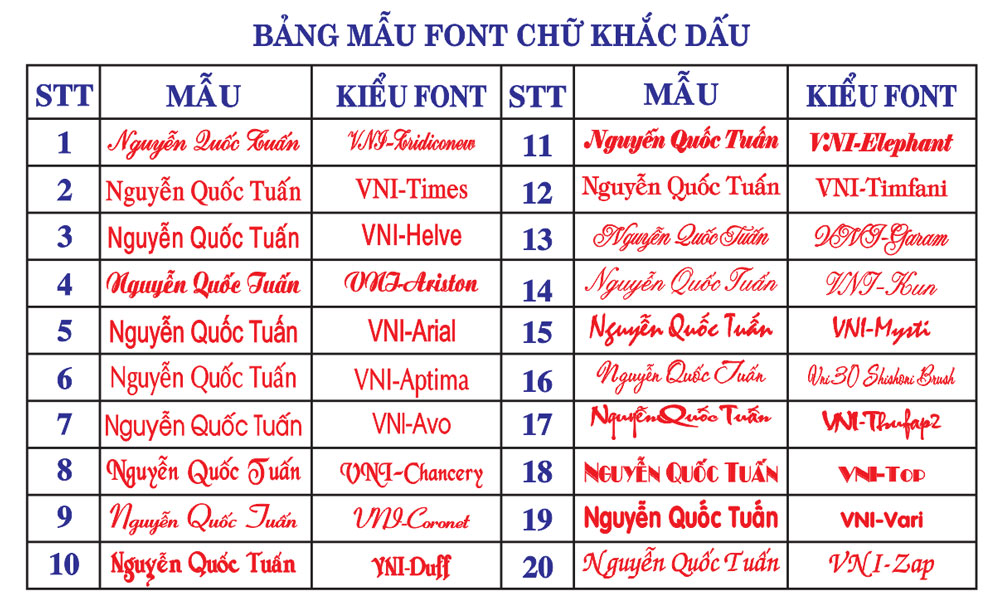
Font chữ con dấu là nhóm phông chữ kỹ thuật chuyên dùng trong lĩnh vực khắc dấu cao su, khắc laser mộc dấu công ty, dấu chức danh và các mẫu dấu phê duyệt bản vẽ hoàn công. Sở hữu cấu trúc nét chữ gọn gàng, độ dày nét chuẩn xác và tính chuẩn mực cao, việc sử dụng đúng font chữ làm con dấu giúp các kỹ sư, kiến trúc sư và doanh nghiệp thể hiện tính pháp lý minh bạch trên các hợp đồng thi công, biên bản nghiệm thu hay hồ sơ thiết kế nhà lắp ghép.
Độ sắc nét và cấu trúc kỷ luật của các dòng font chữ con dấu
Điểm giá trị của dòng font con dấu nằm ở tính dễ đọc và khả năng chịu lực cơ học khi chuyển đổi thành dạng con dấu cao su hoặc con dấu liền mực. Khác với các phông chữ trang trí rườm rà, các kiểu chữ dùng để khắc dấu thường sở hữu các đường thẳng dứt khoát, không có chân phụ thừa thãi hoặc sử dụng dạng chữ thảo mực thước đối với con dấu chữ ký.
Sự ổn định về mặt thị giác của dòng font này giúp khẳng định tính xác thực và thẩm quyền của người ký duyệt hồ sơ. Khi xuất hiện trên các góc bản vẽ kỹ thuật CAD dưới dạng con dấu vuông thẩm tra hay mộc tên chức danh kỹ sư giám sát, phông chữ mang lại cảm giác nghiêm túc, chuẩn mực.
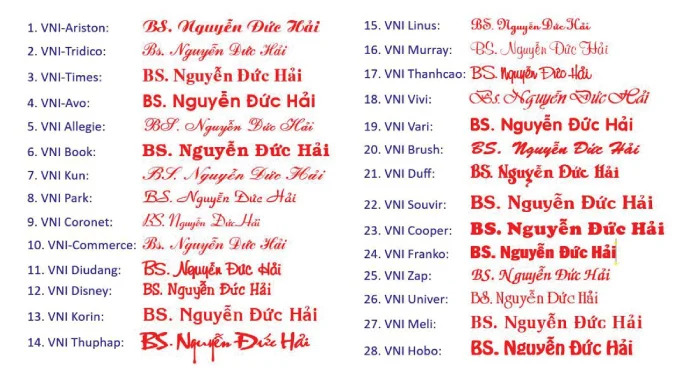
| Nhóm con dấu | Đặc tính phông chữ | Mục đích phù hợp |
|---|---|---|
| Dấu tròn doanh nghiệp | Sans-serif đứng, nét đều, gọn gàng | Font chữ con dấu tròn pháp nhân |
| Dấu tên & Chức danh | Chữ thảo mềm mại hoặc chữ in hoa đậm | Font chữ làm mộc tên, chức danh |
| Dấu vuông hoàn công | Condensed Sans, nét hẹp, rõ ràng | Font chữ con dấu vuông bản vẽ |
| Dấu chức vụ kiểm tra | Serif truyền thống hoặc Sans-serif dứt khoát | Dấu đã thu tiền, dấu sao y bản chính |
Tư vấn từ chuyên viên: Khi thiết kế font chữ khắc dấu tròn pháp nhân, bạn nên sử dụng các kiểu chữ không chân dạng đứng (như Arial hoặc Helve) để thông tin công ty uốn cong theo đường tròn được sắc nét.
03 Ứng dụng font con dấu vào công tác quản lý xây dựng
Nhờ tính chuẩn mực và độ nhận diện pháp lý cao, bộ phông chữ này mang lại giá trị thực tế lớn trong khâu hành chính và quản lý thi công công trình hiện đại:
- Khắc dấu mộc tên cho Kỹ sư và Kiến trúc sư: Những nét chữ mực thước của font chữ con dấu tên giúp các cán bộ kỹ thuật đóng dấu xác nhận lên các bản vẽ hiện trường, nhật ký thi công nhà lắp ghép một cách rõ ràng và uy tín.
- Làm dấu vuông Phê duyệt và Hoàn công bản vẽ: Phông chữ dạng condensed khi khắc lên con dấu vuông khung viền sẽ giúp các thông tin về ngày nghiệm thu, đơn vị tư vấn giám sát hiển thị trọn vẹn trong các khung tên bản vẽ AutoCAD.
- Khắc dấu tròn pháp nhân cho Doanh nghiệp: Áp dụng font chữ đóng dấu chuẩn quy định giúp con dấu doanh nghiệp khi đóng lên hợp đồng kinh tế đạt độ sắc sảo, không bị nhòe mực trên các chất liệu giấy in thông dụng.
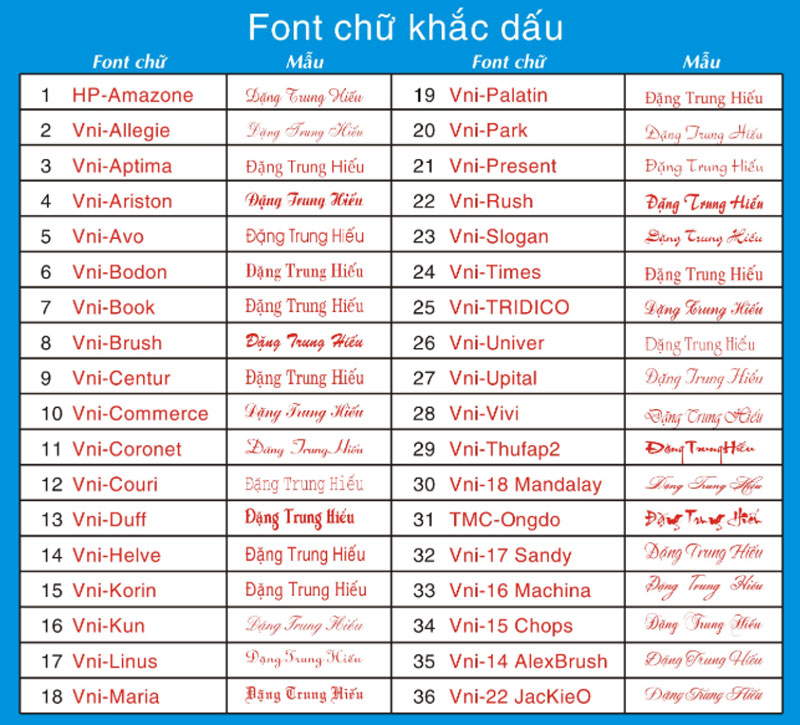
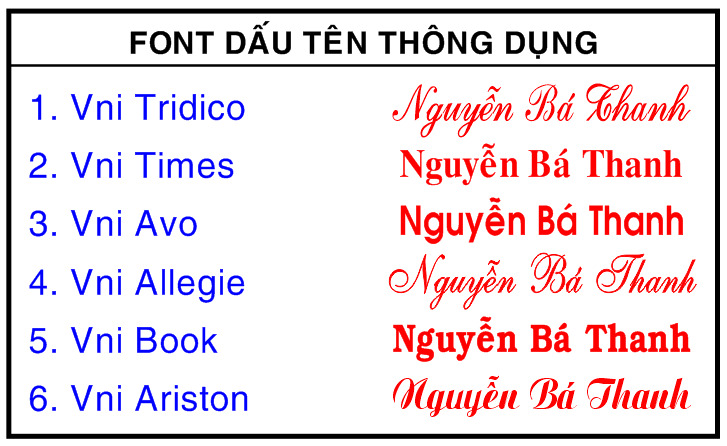
03 Lưu ý bố cục font chữ khắc dấu tên và dấu tròn rõ nét
Để con dấu sau khi gia công cơ học đạt độ sắc nét và không bị lem mực khi sử dụng thực tế, người thiết kế nên lưu tâm một số kinh nghiệm sau:
- Kiểm soát độ dày nét chữ: Khi lập trình khắc laser cao su, nét chữ không được quá mảnh vì sẽ dễ bị đứt gãy dưới lực ép đóng dấu, nhưng cũng không được quá dày vì sẽ hút nhiều mực dầu gây hiện tượng bết dính các chữ cái có vòng kín (như o, e, a).
- Bố trí khoảng cách chữ thông thoáng: Do mực dấu có độ loang nhẹ trên thớ giấy, bạn nên kéo giãn nhẹ khoảng cách giữa các chữ cái để các ký tự không bị dính vào nhau sau khi đóng dấu lên văn bản.